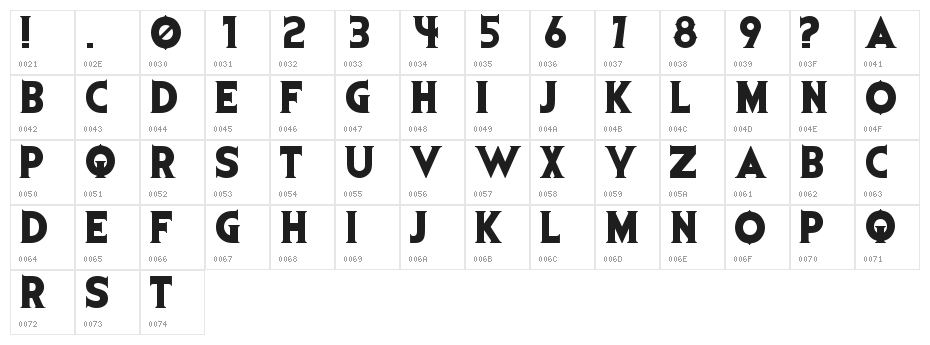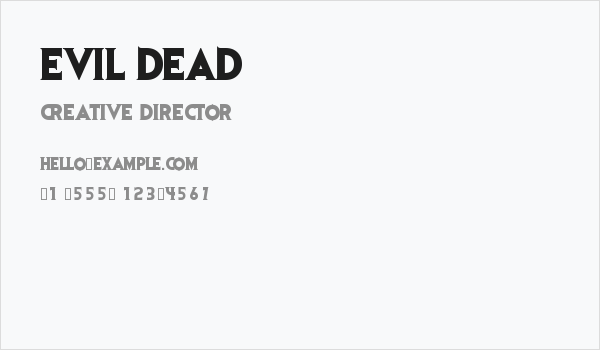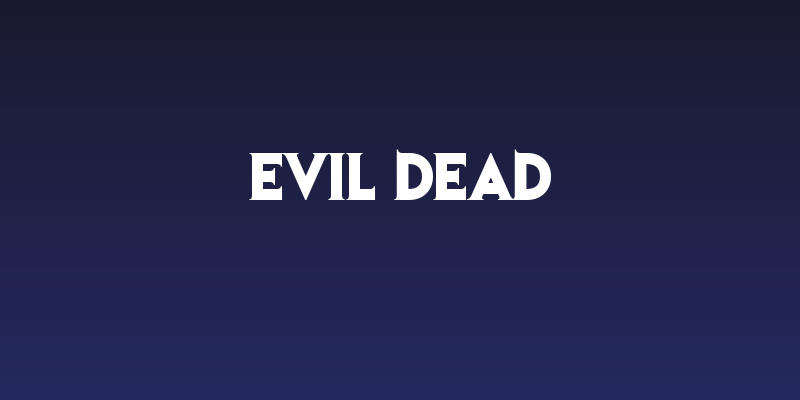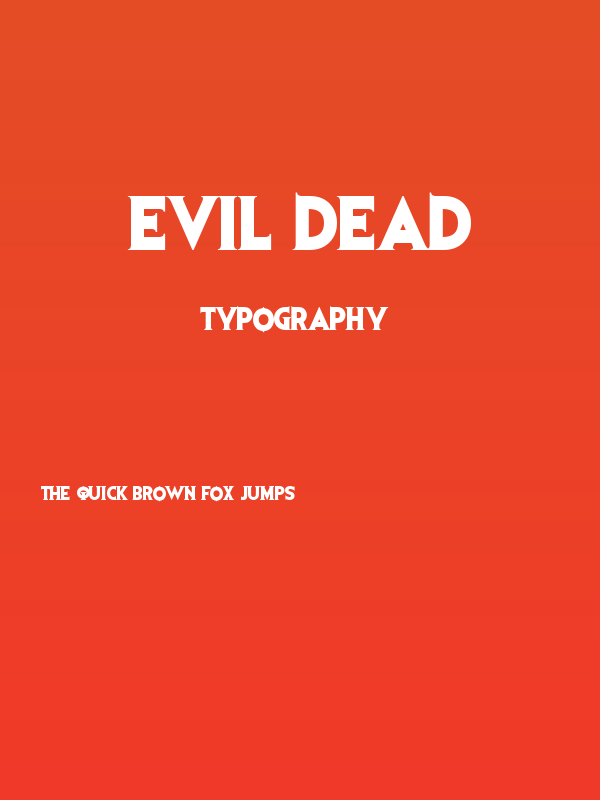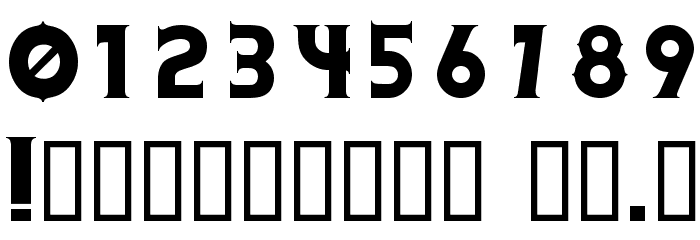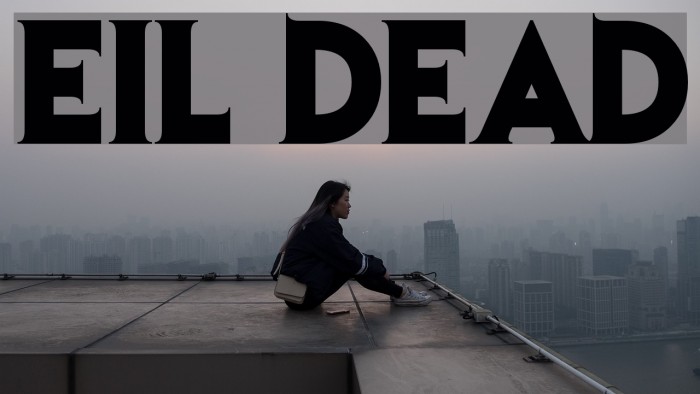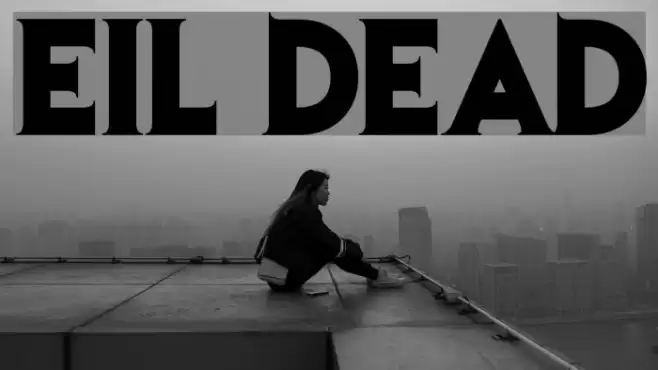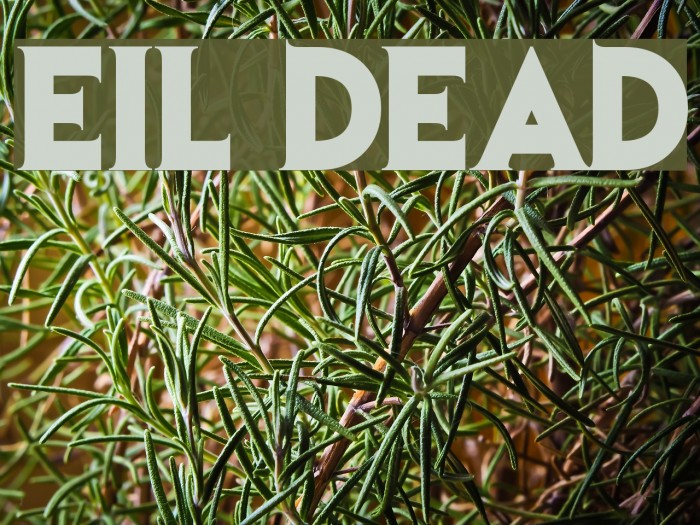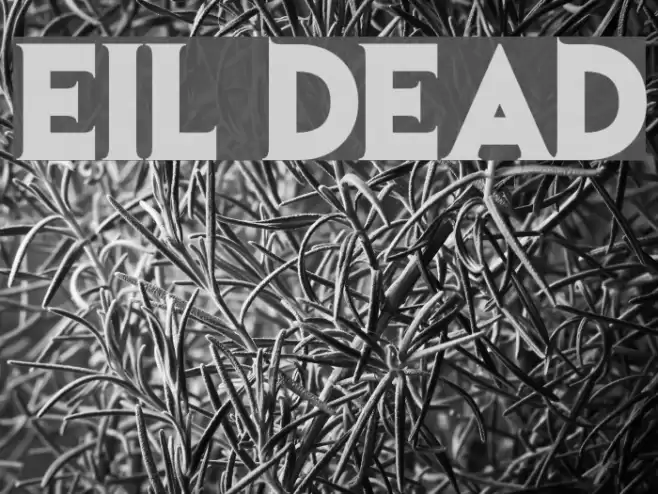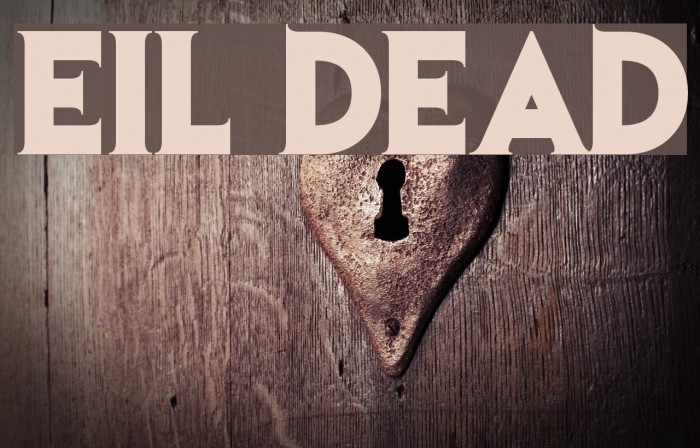
Evil Dead Font
| Projets proposés | Ideal for horror movie posters, Halloween event promotions, themed merchandise, and any project needing a dramatic flair. |